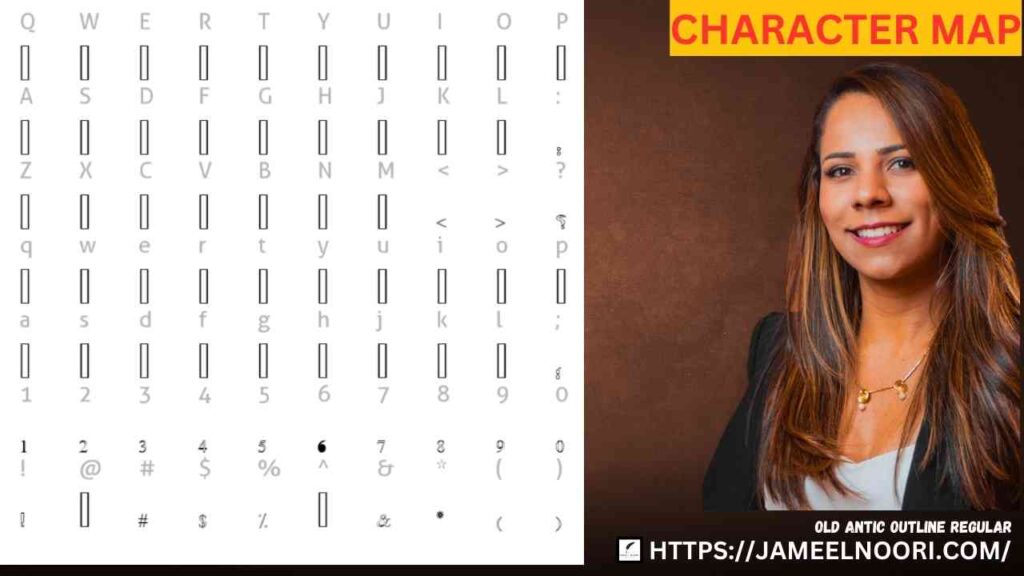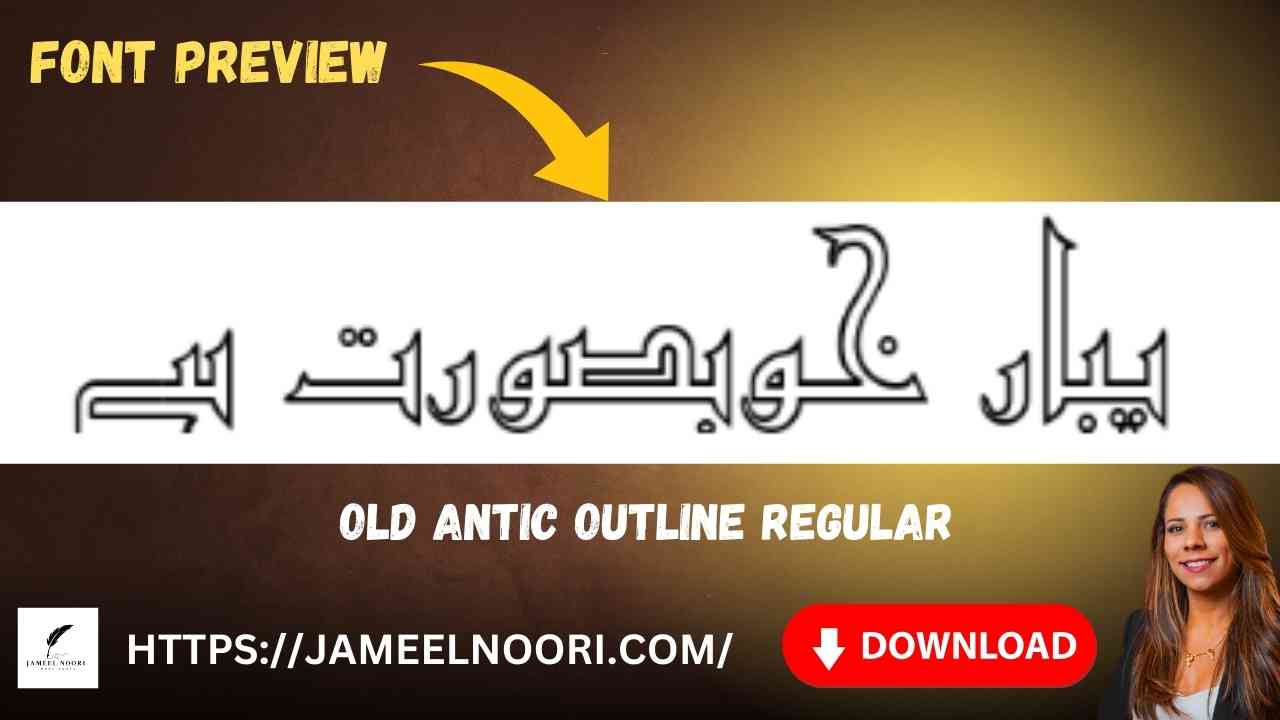
Download Urdu font Old Antic Outline Regular – Complete Guide for Pakistan Users
Introduction – Download Urdu font Old Antic Outline Regular
Aaj kal Pakistan me Urdu fonts ki demand bohot zyada barh gayi hai, specially jab log apni websites, designs ya documents Urdu style me tayar karte hain. Download Urdu font Old Antic Outline Regular aik aisa font hai jo apni unique outline aur stylish look ki wajah se popular hai. Ye font free available hai aur easily download kiya ja sakta hai. Is article me hum step-by-step guide aur features discuss kareinge.
Technical Details of Download Urdu font Old Antic Outline Regular
Font NameOld Antic Outline Regular
StyleRegular
UsageUrdu Typing, Titles, Designs
Features of Download Urdu font Old Antic Outline Regular
Old Antic Outline Regular aik Regular TrueType Font hai jo Urdu aur stylish outline text ke liye best choice hai. Iske kuch khas features ye hain:
• Unique outline style jo heading aur title ke liye perfect hai
• Urdu writing aur graphic designing dono ke liye suitable
Popularity of Download Urdu font Old Antic Outline Regular
Why Choose Download Urdu font Old Antic Outline Regular – Expert Choice
• Best for Urdu websites: Blog aur news sites ke liye perfect
• Stylish look: Design projects me unique outline create karta hai
Agar aap apni Urdu typing aur designing ko ek stylish touch dena chahte hain, to Download Urdu font Old Antic Outline Regular aap ke liye best choice hai. Ye free available hai aur Pakistan me specially Urdu users ke liye design aur writing ko enhance karta hai. Lahore, Karachi aur Islamabad ke bohot se designers already is font ko use kar rahe hain.
What type of font is Old Antic Outline Regular?